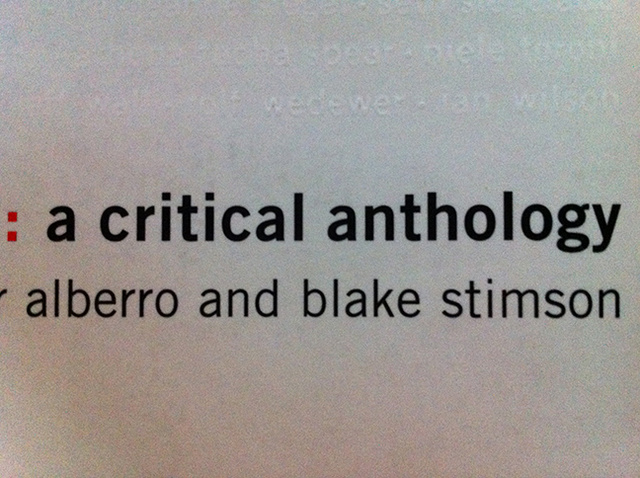
Hallo. Weiß jemand, was das ist?
Sieht mir wie Trade Gothic Bold No. 2 aus …
Aber unterscheiden sich die beiden denn?
Edit: Wie man diesem pdf entnehmen kann, ist es die "Trade Gothic Bold Two".
Ja richtig, in der News Gothic ist die untere Punze im kleinen G ist nicht so oval.